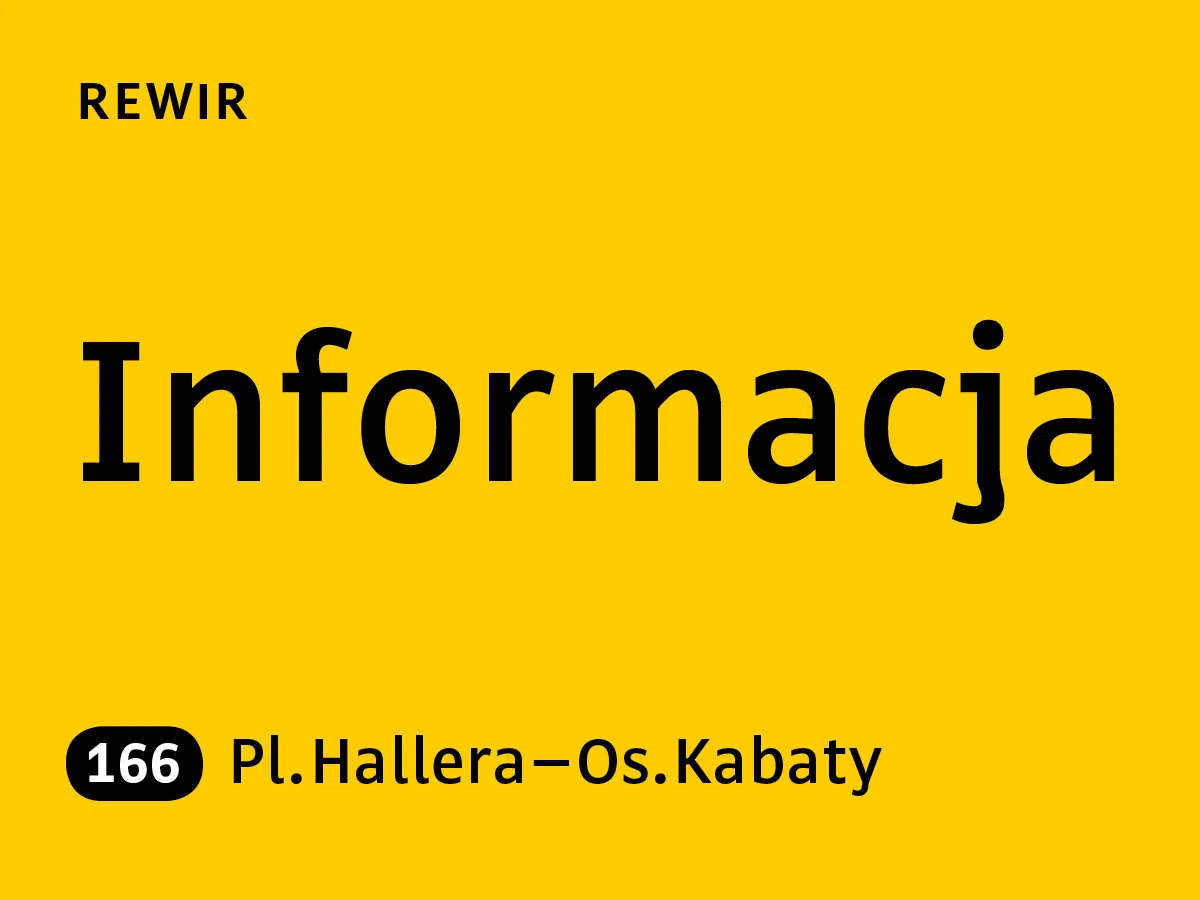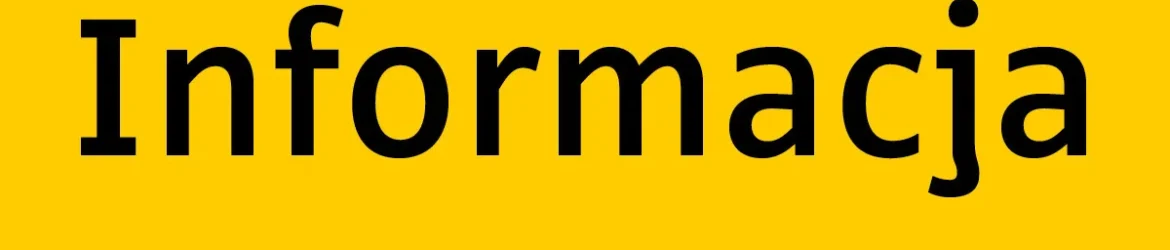
Rewir Typeface – Download Grátis
A página de download para a fonte Rewir Typeface apresenta uma nova opção para designers digitais interessados em projeções arquitetônicas modernas e legíveis. Desenvolvida pelo designer Robert Jarzec, Rewir é inspirada nas formas de letras de um pequeno sinal encontrado no quintal de uma casa de apartamentos em Varsovia. Esta fonte foi projetada originalmente como uma proposta para uso corporativo em placas e sinais na arquitetura oficial das construções públicas e estaduais. O design de Rewir incorpora a história dos padrões de escrita de Varsovia, combinando isso com as necessidades exigentes de uma cidade moderna. Os traços da letra são inspirados em um pequeno sinal localizado em uma residência. Afonte é extremamente legível, mesmo sob condições de visão variadas. Ela pode ser usada para placas oficiais, cartões de visita, informações sobre transporte público e mais. Rewir oferece uma solução criativa para a utilização das letras no contexto do design urbano moderno. Com seus traços dinâmicos e formas limpas, esta fonte é ideal para uso em qualquer aplicativo que precise de letras legíveis em ambientes urbanos movimentados.